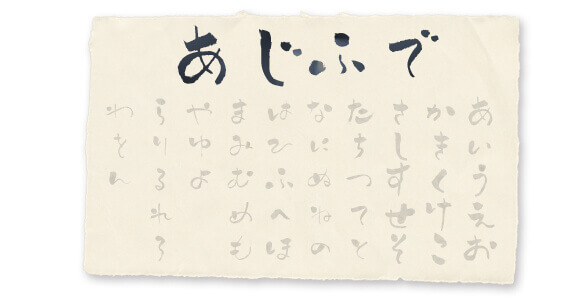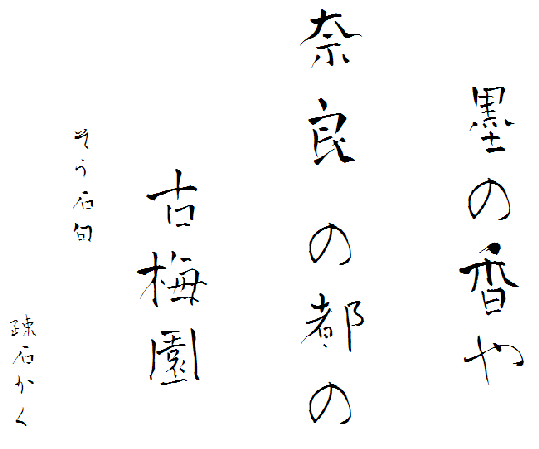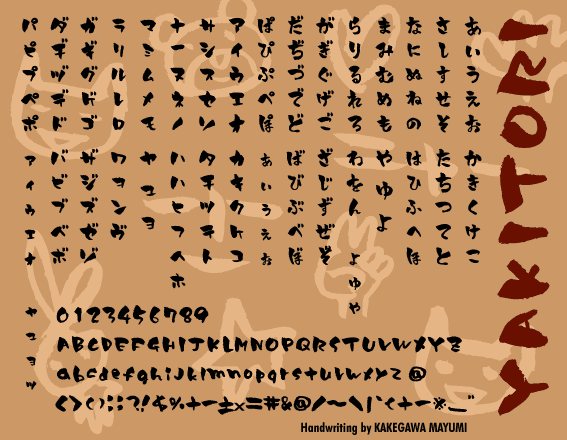
無料でダウンロード可能な習字フォント10個
筆字の特徴である「はらい」「とめ」「はね」が再現された、無料でダウンロードできる習字フォントをまとめました。年賀状や暑中お見舞いの作成に最適なのはもちろんのこと、中には表彰状(賞状)や、お中元・お歳暮に掛けるのし紙の名入れに最適なフォントもございます。各ライセンスをご確認の上ご利用ください。
KUROTAKE
半紙に筆でベチャ!と墨汁を垂らしたような墨滴フォント。
あじふでフォント
筆で書いた味のあるひらがなフォント。収録されている文字はひらがなのみ。料亭のお品書きなど和風のデザインにピッタリ。
ジンへなかな
筆ペンで書いた文字を再現したフォント。ささっとラフに書いたような字体が特長。
ジンへな墨流-RCF
ヘナヘナっとした感じの毛筆風フリーフォント。居酒屋などのお品書きにピッタリ。
ふわふで
やわらかい筆で書いたような筆文字フォント。ふわふわな可愛いデザインに。
やきとりフォント
焼き鳥屋さんのメニューに使われていそうな手書きフォント。太めの筆で書かれているので力強い雰囲気が伝わってくる文字。
衡山毛筆フォント
書家の青柳衡山氏が揮毫及び作成したフォント。登録文字数は約13,000字。(Windows TrueTypeフォントの場合)
青柳衡山フォントT
書家の青柳衡山氏が揮毫及び作成したフォント。JIS非漢字、JIS第一水準漢字を収録。
青柳疎石フォント
書家の青柳疎石氏が字母を書き、青柳衡山氏がフォント化した毛筆フォント。JIS非漢字、JIS第一水準漢字、JIS第二水準漢字が収録。
青柳隷書しも
書家の青柳衡山氏が揮毫したものを、SIMO氏が作成したフォント。JIS第二水準まで収録。